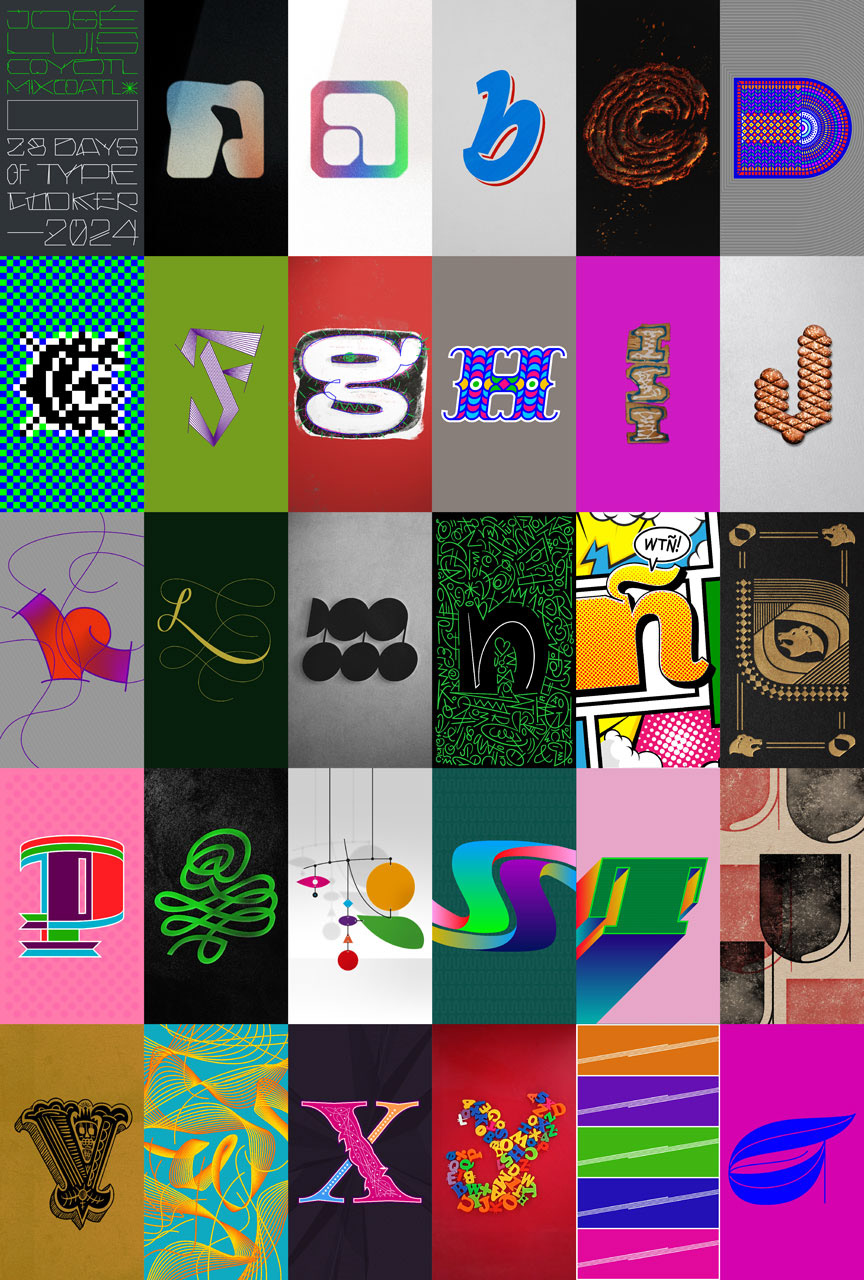
28 DAYS OF TYPECOOKER 2024
Serie de letras desarrolladas para el reto 28 días de TypeCooker 2024 del colectivo Letrástica, en el que se diseñaron durante un mes, una letra por día, en diferentes estilos con carácter y estilo gráfico expresivos, experimentando con la forma y la estructura tipográfica desde una forma de diseño más personal desde las directrices de la dinámica TypeCooker, lo que hizo una manera de pensar cada reto de forma más dinámica.